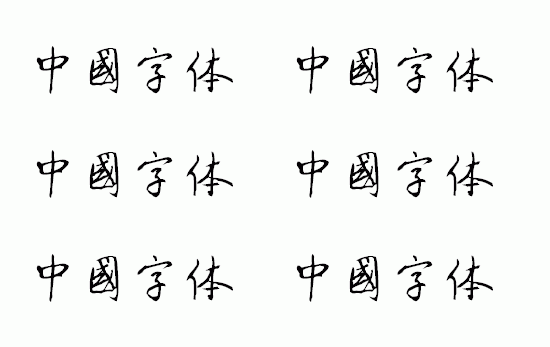
劉炳森字體試用版
劉炳森字體試用版字體由綠色資源網(wǎng)為您提供的一款書(shū)法字體,劉炳森以隸書(shū)立足當(dāng)代書(shū)壇,是當(dāng)今最著名的隸書(shū)書(shū)法家,但也是最有爭(zhēng)議的書(shū)法家,喜歡劉炳森先生作品的朋友可以在此下載使用
劉炳森字體預(yù)覽
劉炳森字體